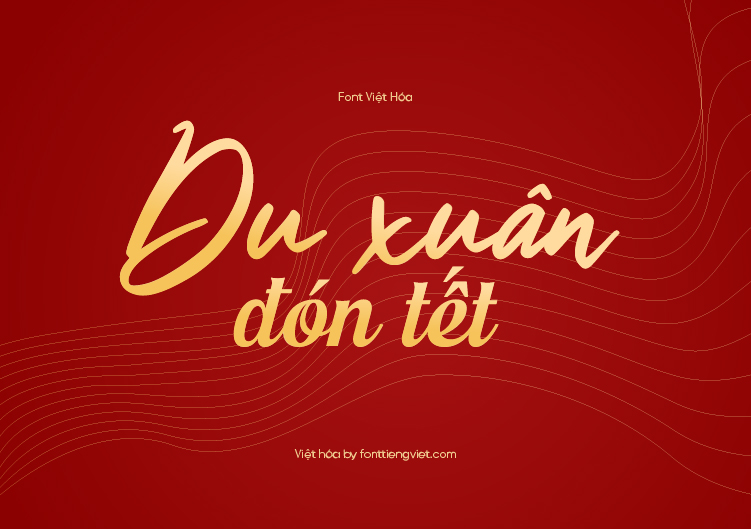
Font việt hóa 1FTV VIP Firegoods – Tết
Giới thiệu về Font việt hóa 1FTV VIP Firegoods – Tết
Trong thế giới thiết kế đồ họa chuyên nghiệp, việc lựa chọn một bộ Font Miễn Phí phù hợp chính là chìa khóa để truyền tải linh hồn của tác phẩm. Đặc biệt, khi những ngày Tết cổ truyền đang đến gần, nhu cầu về các phông chữ mang đậm nét văn hóa Việt Nam lại càng trở nên cấp thiết hơn bao giờ hết. Font việt hóa 1FTV VIP Firegoods – Tết nổi lên như một giải pháp hoàn hảo cho các nhà thiết kế muốn kết hợp giữa phong cách hiện đại và giá trị truyền thống. Bộ phông chữ này không chỉ đơn thuần là những đường nét trên mặt giấy, mà còn là sự kết tinh của nghệ thuật sắp đặt chữ viết, giúp các câu chúc năm mới trở nên ý nghĩa và sinh động hơn. Được tối ưu hóa hoàn toàn cho bảng mã tiếng Việt, người dùng có thể yên tâm sử dụng mà không lo lỗi dấu hay sai lệch định dạng khi soạn thảo văn bản hoặc thiết kế ấn phẩm quảng cáo Tết.
Đặc điểm nổi bật của Font việt hóa 1FTV VIP Firegoods – Tết
Bộ phông chữ này gây ấn tượng mạnh mẽ nhờ cấu trúc đường nét chắc chắn nhưng không kém phần uyển chuyển. Mỗi ký tự trong Font việt hóa 1FTV VIP Firegoods – Tết đều được chăm chút tỉ mỉ để phản ánh đúng tinh thần của những lễ hội rộn ràng. Điểm đặc biệt của nó nằm ở khả năng biến hóa linh hoạt, phù hợp từ các banner quảng cáo đường phố cho đến các tấm thiệp chúc mừng tinh tế. Các nhà thiết kế tại Việt Nam đánh giá cao bộ font này bởi sự hài hòa giữa độ dày của nét chữ và khoảng cách giữa các ký tự, tạo nên sự dễ đọc ngay cả khi quan sát từ xa. Đây thực sự là một công cụ đắc lực để tạo nên bản sắc riêng cho các chiến dịch truyền thông dịp đầu xuân năm mới.
Cách ứng dụng Font việt hóa 1FTV VIP Firegoods – Tết trong thiết kế
Việc sử dụng Font việt hóa 1FTV VIP Firegoods – Tết rất đa dạng và không giới hạn trong một khuôn khổ nhất định. Trong môi trường học đường, các em học sinh và giáo viên có thể dùng phông chữ này để trang trí bảng tin lớp học hoặc thiết kế các bài thuyết trình về chủ đề ngày Tết quê em. Sự gần gũi và ấm áp mà phông chữ này mang lại sẽ giúp các em cảm nhận rõ hơn không khí lễ hội. Đối với các doanh nghiệp, đây là lựa chọn hàng đầu cho các thiết kế bao bì sản phẩm quà tặng, bao lì xì hay các biển hiệu khuyến mãi cuối năm. Việc kết hợp font chữ này với các tông màu đỏ, vàng chủ đạo sẽ tạo nên một tổng thể vô cùng bắt mắt và chuyên nghiệp, thu hút sự chú ý của khách hàng ngay từ cái nhìn đầu tiên.
Lưu ý khi sử dụng phông chữ Việt hóa
Dù Font việt hóa 1FTV VIP Firegoods – Tết rất đẹp và tiện dụng, người dùng cũng cần lưu ý một số điểm để đạt hiệu quả thẩm mỹ cao nhất. Thứ nhất, tránh việc nhồi nhét quá nhiều phông chữ khác nhau trong cùng một thiết kế để không gây rối mắt. Thứ hai, hãy chú ý đến độ tương phản giữa màu chữ và màu nền để đảm bảo nội dung luôn hiển thị rõ ràng nhất. Cuối cùng, vì đây là bộ phông chữ mang phong cách lễ hội, nó sẽ phát huy tối đa sức mạnh khi được đặt trong các bối cảnh trang trọng hoặc rộn ràng của những ngày Tết. Sự sáng tạo là vô tận, nhưng sự tinh tế trong cách chọn font luôn là yếu tố quyết định sự thành công của một tác phẩm nghệ thuật đồ họa chuyên nghiệp.
Kết luận về bộ Font việt hóa 1FTV VIP Firegoods – Tết
Có thể khẳng định rằng, Font việt hóa 1FTV VIP Firegoods – Tết là một trong những tài nguyên quý giá dành cho cộng đồng yêu thiết kế tại Việt Nam. Nó không chỉ giúp giải quyết bài toán về hiển thị tiếng Việt mà còn mang lại giá trị thẩm mỹ vượt trội cho các sản phẩm sáng tạo. Hy vọng với những chia sẻ trên, bạn sẽ có thêm cảm hứng để tạo ra những tác phẩm tuyệt vời đón chào năm mới. Đừng quên truy cập vào hệ thống của chúng tôi để cập nhật thêm nhiều bộ Font Miễn Phí, Font Việt Hóa, Font việt hóa 1FTV VIP Firegoods – Tết chất lượng khác. Chúc bạn có những trải nghiệm thiết kế thú vị và thành công rực rỡ với những ý tưởng độc đáo của mình trong mùa xuân này!